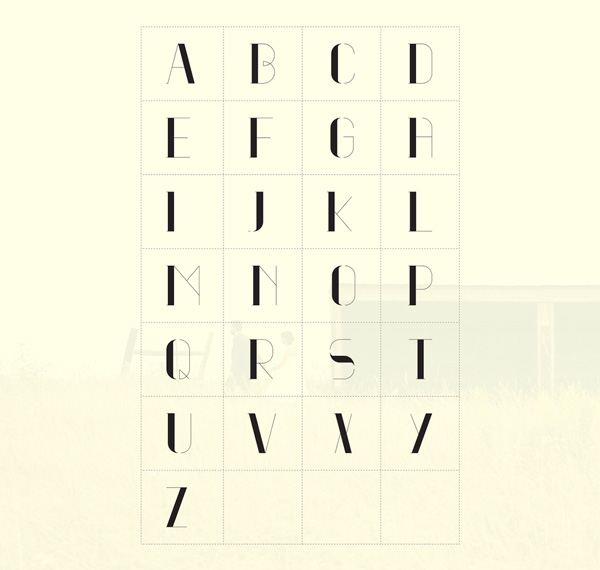
Os traigo una tipografía con serifas gratuita y muy útil para cabeceras y resaltados en caja alta. La licencia es libre así que podéis utilizarla tanto para proyectos personales como comerciales. Para descargarlo pulsad sobre la imagen o en el link del pie de la entrada. Espero que os sirva y recordad que los like y los follow ayudan mucho así que visitadnos enTwitter yFacebook.También nos podéis encontrar en Flipboard buscando nuestra revista El Arquitecto de Ilusiones.